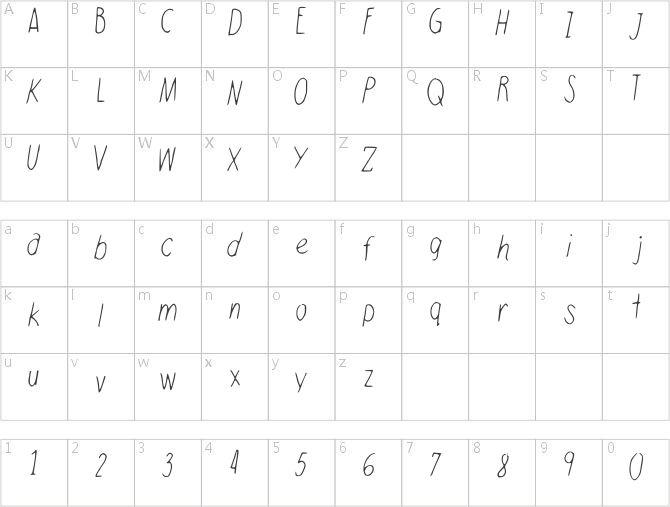
WalkonFire 詳情頁(yè)
WalkonFire字體字庫(kù)是一款讓人賞心悅目、百看不厭的英文字體,適合各類(lèi)廣告和產(chǎn)品包裝設(shè)計(jì)應(yīng)用,字體大小0.02MB,格式為ttf字體,上傳用戶是sygyve520,作者/版權(quán)方為未知